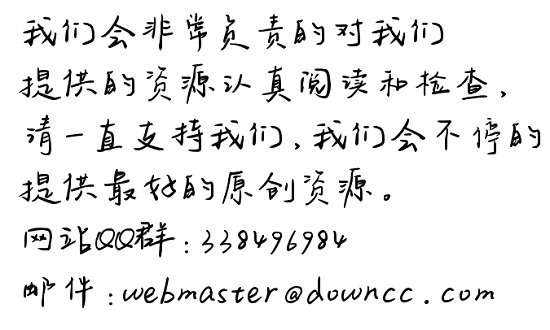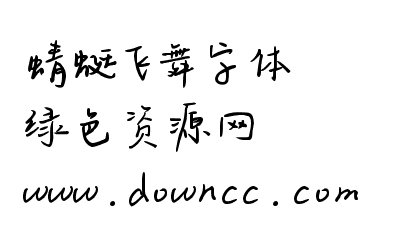
蜻蜓飛舞體帶給人安靜夏日午后的一股閑適心情,在這營造的靜謐氛圍中,微游字跡濃淡相間,更顯生機(jī)盎然之態(tài),不一樣的閱讀體驗(yàn),只需在綠色資源網(wǎng)下載即可擁有!
蜻蜓飛舞體特色
本字庫是在國家標(biāo)準(zhǔn)簡體字庫GB2312所包含6763漢字的基礎(chǔ)上,又增加了近200常用字,已經(jīng)覆蓋了大陸99.75%的漢字使用頻率,足以滿足日常需求。
設(shè)計(jì)背景
在那些安靜的閑暇歲月中,沒有喧囂,沒有紛擾,有的只是蜻蜓飛舞般的輕盈和歡快。靜下心來,做一只快樂的小蜻蜓。
綠色資源網(wǎng)小編點(diǎn)評
蜻蜓飛舞字體,采用了硬筆書法字體的風(fēng)格,給人清新雅致的活潑之氣,文字沒有矯揉造作之感,還原古色生香的獨(dú)特魅力,可以使用在藝術(shù)設(shè)計(jì)、包裝設(shè)計(jì)等多種產(chǎn)品中。